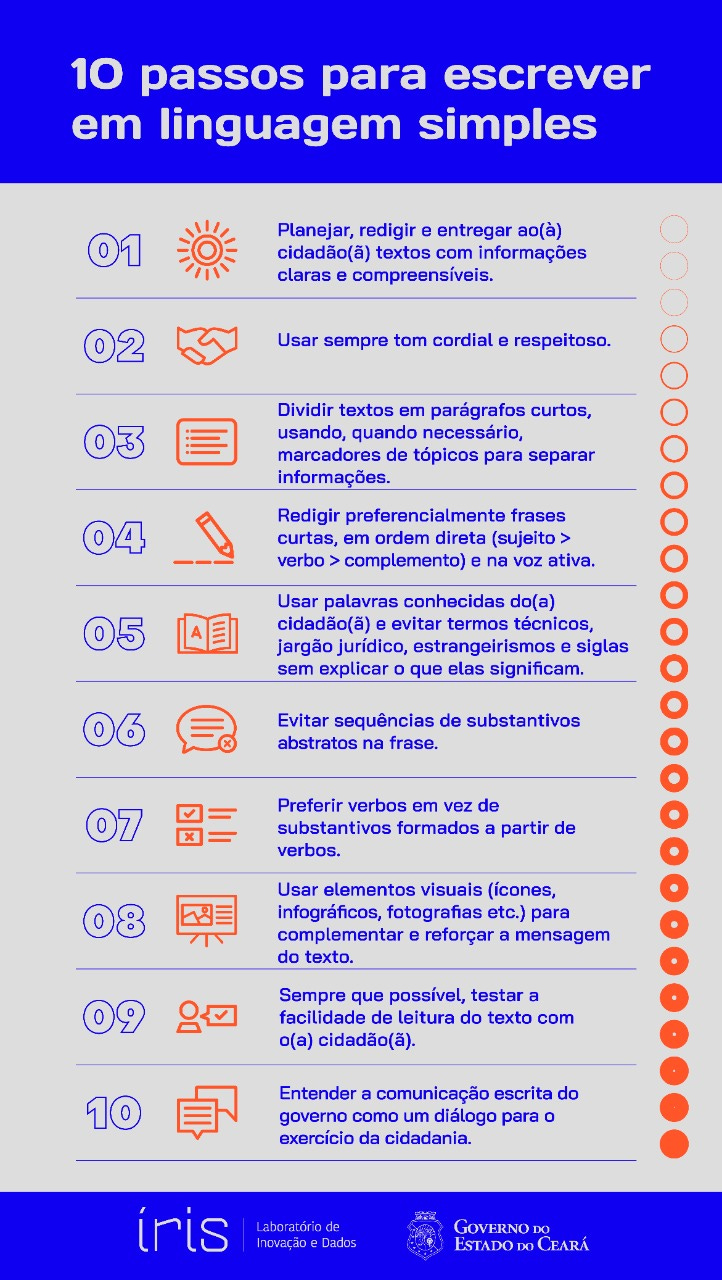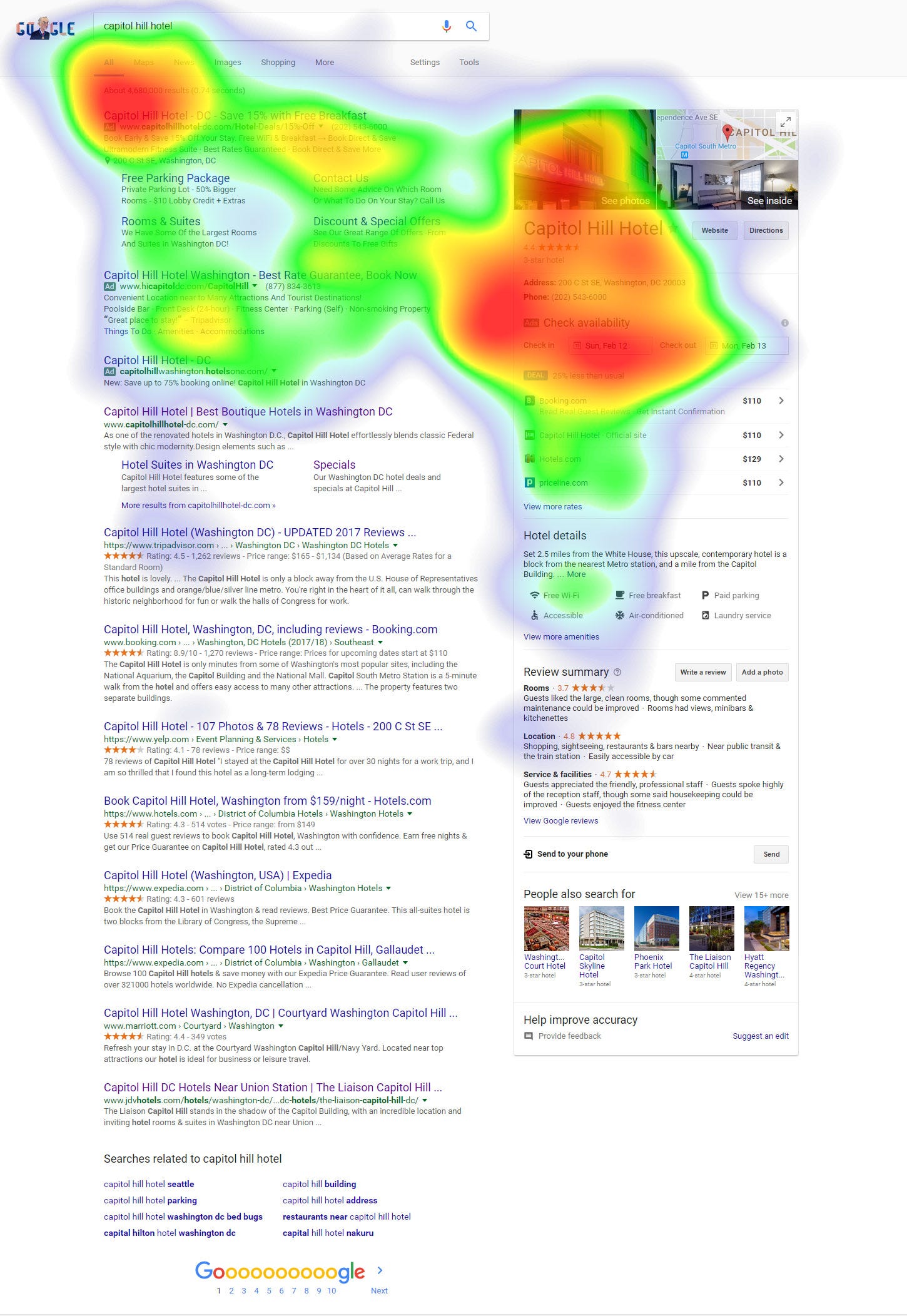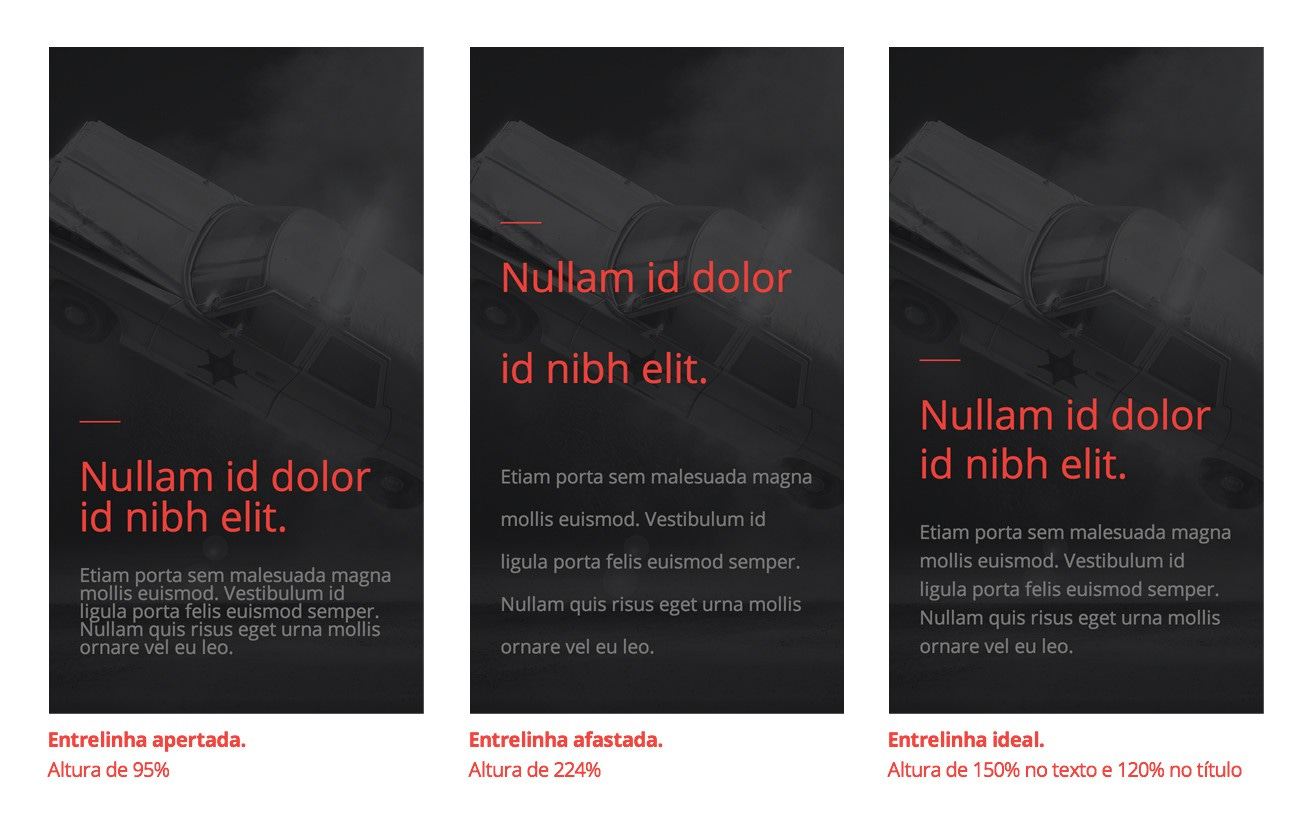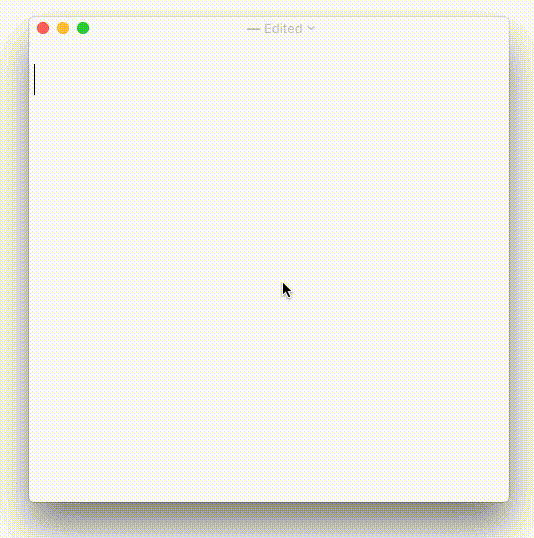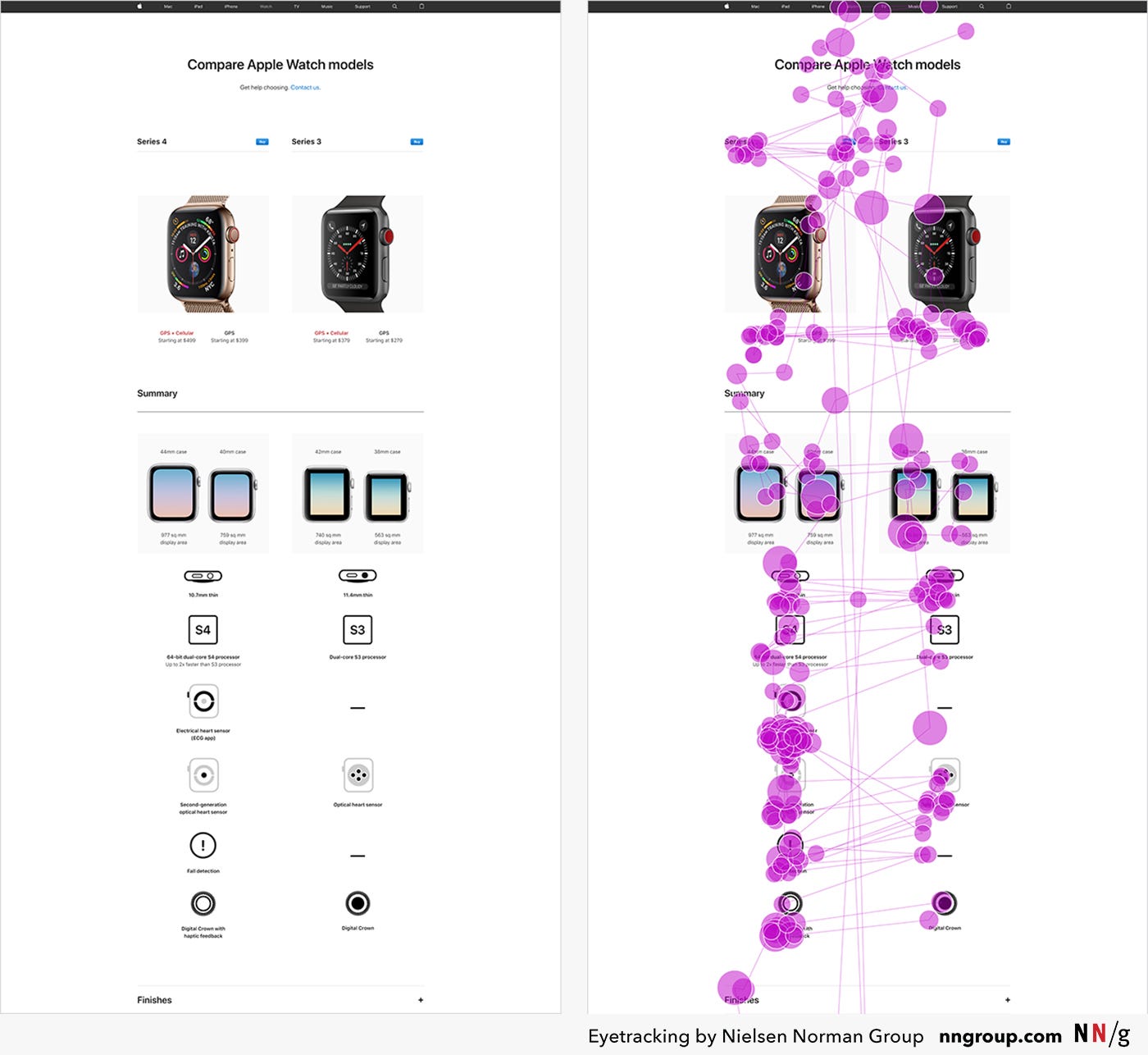
Tipo Aquilo #46 – UX: o usuário não lê 🖥 👁
É isso. O usuário não lê mesmo. Durma com essa, boa noite e boa sorte.
(pausa dramática)
Ok, é um pouco mais complicado, já que… bem… você está lendo algo impresso com luz numa tela de pixels luminosos, um dos piores meios de leitura que a tecnologia pode oferecer. É agressivo para o sistema ocular, mais difícil de ser feito numa postura correta, e pouca gente sabe tratar direito um texto lido num display. Os computadores de mesa, de colo e de mão oferecem vários confortos que mitigam o desconforto da leitura em tela; nós comunicamos, pedimos comida às 3h da manhã (como todo paulista ama dizer que pode, mesmo que não faça), recebemos notícias, mandamos notícias, trabalhamos e divertimo-nos quando dá tempo.
Entre os UX designers, existe o desafio de entregar para o usuário uma tarefa que demanda a leitura de um texto para que esta seja cumprida. Existe também a frustração quando o usuário faz o contrário do que a tarefa exige porque ele não leu o texto que dizia com todas as letras: não faça isso. Isso é recorrente, nem sempre dá pra confiar a ilustrações e ícones a complexidade de uma informação que só um texto bem construído é capaz de lidar. Só que, se o usuário não lê, como eu fiz questão de dizer no começo do texto, como fazer para que o usuário leia? E se for importante, mas o usuário deixar de lado, o que se faz? Sexta, às dez da noite, no Globo Repórter. ;)
Todo designer já passou pela tristeza de ver que o usuário deixa de ler informações cruciais para a tarefa que está realizando. “Era só o usuário ter lido bem ali”, diz o padawan entre os amigos na sexta à noite na call antes do fim-de-semana. Era sim, de fato. Só que, como eu disse no começo, a leitura em tela é ruim para os olhos. As telas modernas de LCD e LED são menos agressivas do que os antigos monitores de tubo, mas ainda são desconfortáveis, tendem a causar fadiga ocular e afetam até a compreensão do texto. O modo escuro de interfaces gráficas e o night shift, que reduz o uso de cores azuladas na tela, são recursos que ajudam em contextos de pouca luminosidade, mas não resolvem o problema.
Posto assim, chega a ser injusto que um aplicativo ou site exija do usuário que ele leia algo na tela para que a pessoa tenha o que ela deseja. Além do problema do desconforto, estamos sempre competindo pela atenção da pessoa: se a interface que a gente propõe não é atrativa e não cumpre uma promessa de forma simples, o usuário pula para outro app, outro site, qualquer outra solução que pareça mais compreensível. Aliás, guarde o verbo pular; vamos usar bastante por aqui porque ele se aplica a diversos comportamentos do usuário. Certos pulos são inevitáveis; porém, um dos segredos para garantir que o usuário não pule para outro produto ou marca é a leiturabilidade.
Primeiro, vamos falar dos pulos inevitáveis. A própria leitura é feita de “pulos”, os sacádicos. Conforme as pessoas se alfabetizam e acostumam-se com ler o tempo todo, elas deixam de ler letra por letra, e até mesmo palavra por palavra. Em busca de eficiência, o cérebro processa o texto buscando por palavras mais importantes, como verbos e substantivos, e depois busca por conjunções, preposições, pronomes e outros constructos gramaticais ao redor. Esses movimentos de saltos e vai-e-vem entre palavras são chamados de sacádicos; acontecem com qualquer fonte que você usar, e ficaram evidentes a partir de estudos com dispositivos de eye tracking, que monitoram os movimentos dos olhos durante uma atividade.
Para que os sacádicos aconteçam, as pessoas deixam a leitura linear para rastrear as palavras e suas formas. Isso acontece quando você lê um site de internet, um aviso no meio da rua, um artigo de jornal ou uma página de livro. Sabe aquelas imagens de correntes de zap que dizem que você consegue ler certas palavras mesmo que a ordem das letras esteja ligeiramente diferente? Isso acontece porque nos acostumamos com as formas das palavras, em vez de letra-por-letra, em nome da eficiência. O cérebro adora fazer tudo da maneira mais econômica possível, e confia em certas letras com formas mais reconhecíveis para combinar a palavra que está lendo com a imagem que ele espera.
Falando especificamente de telas luminosas e interfaces digitais, os saltos são ainda maiores porque os usuários estão constantemente rastreando a tela em busca de algo relevante. Uma pesquisa do NN/g chama esse padrão de “cortador de grama”, em que o usuário alterna o foco de um lado para o outro em busca da informação que está procurando. Ao encontrar uma palavra interessante, o usuário rastreia ao redor, começa uma leitura rápida, e prontamente muda para outro canto da tela. Mapas de calor feitos com estudos de eye tracking mostram que é comum o usuário começar a ler e abandonar a leitura quando sente que a informação desvia do que ele está procurando, ou que apenas não é importante no momento.
Quando estudamos tipografia num aspecto macro, chegamos aos conceitos de legibilidade e leiturabilidade. Aprendemos que legibilidade diz respeito à facilidade de reconhecer letras num contexto, e leiturabilidade (do inglês readability) refere-se ao quão confortável é a leitura desse texto. Só que leiturabilidade vai além de um texto bem diagramado: segundo William DuBay, o termo abrange vários fatores de facilidade de leitura além do design, como a organização, escolha de conteúdo e de estilo de escrita, de acordo com a escolaridade, interesse e motivação do público leitor. Nenhuma escolha de fonte ou entrelinha salva um texto mal escrito para o público desejado.
Autores como DuBay e Rudolf Flesch foram pioneiros em defender a redação de textos acessíveis a diversos públicos, como crianças e adultos com diferentes níveis de alfabetização. Algumas diretrizes ajudam a melhorar a leiturabiliade de um texto, como o uso de palavras mais curtas e familiares ao leitor, sentenças mais simples com linguagem neutra, ortografia e pontuação corretas e organização por listas de tópicos ou passo-a-passo. É algo que os designers deviam advogar e também estar atentos, ao invés de apenas delegar isso a redatores e UX writers. Adequar a complexidade textual ao público-alvo também é uma decisão de design.
É compreensível que, na maioria das situações, o designer não é autor dos textos que trabalha. O designer não muda a prosa de um escritor ou a redação vinda da agência publicitária, tendo apenas a dimensão visual da leiturabilidade para trabalhar. Nesses casos, a gente busca opções de tipografia que entregam palavras mais rastreáveis — geralmente, com o “a” de dois andares, distâncias confortáveis entre linhas, hierarquia visual clara e o uso consciente de pesos regular e negrito para que os destaques pontuais sejam evidentes. Geralmente, fontes sem serifa funcionam melhor para textos que precisam ser rastreados, ao invés de lidos em sequência. Isso funciona mais como conselho do que como algo cientificamente provado; segundo essa hipótese, as serifas distraem o cérebro durante o rastreamento.